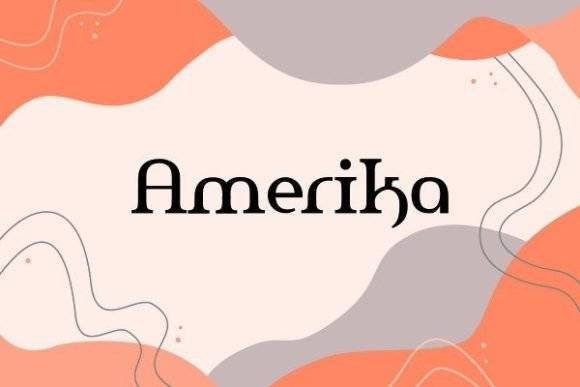
Fonte Amerika para artesanato, logotipos e projetos de impressão.
Amerika é uma fonte visualmente impactante, ideal para artesanato, criação de logotipos e materiais impressos de grande impacto. Seu notável equilíbrio entre estrutura geométrica e estilo artístico a torna perfeita para criar identidades visuais memoráveis para marcas, sinalização e embalagens.
Esta fonte oferece linhas limpas e formas ricas em caracteres, projetadas para comunicar força, clareza e impacto em plataformas físicas e digitais. Ideal para criadores que buscam amplificar suas mensagens por meio de tipografia marcante.
A versatilidade do Amerika em termos de layout e escala permite que ele se adapte de logotipos minimalistas a designs de pôsteres detalhados sem perder a presença.
- Estilo arrojado com uso flexível
- Ideal para impressão, identidade visual e sinalização.
- Identidade visual forte em formatos pequenos ou grandes.
P: Que tipo de fonte é Amerika?
A: Amerika é uma fonte moderna e arrojada, criada para artesanato, logotipos e layouts de impressão impactantes.